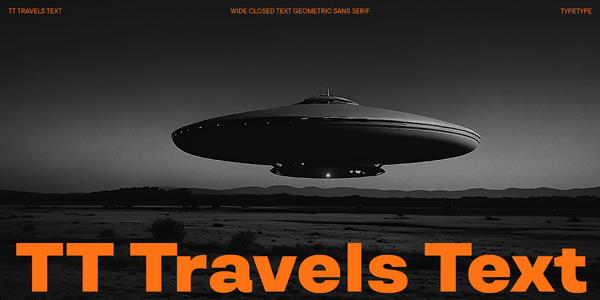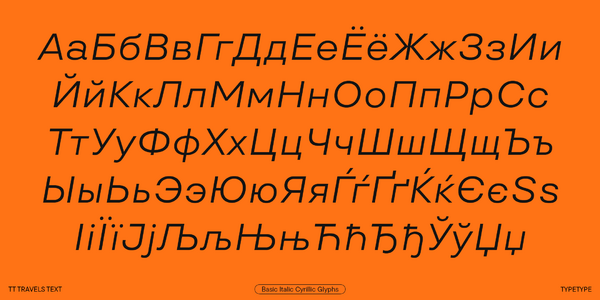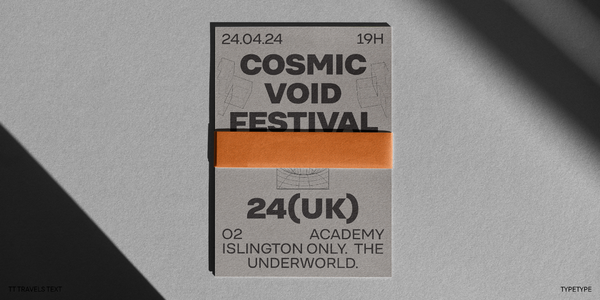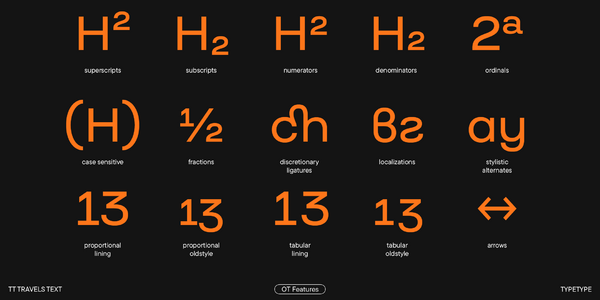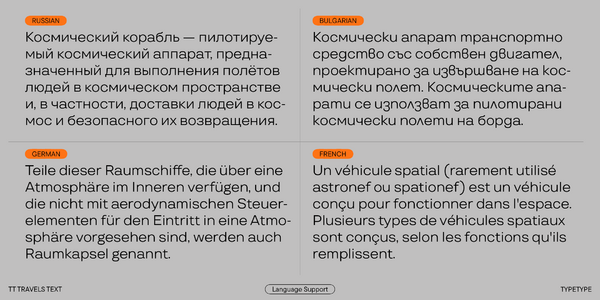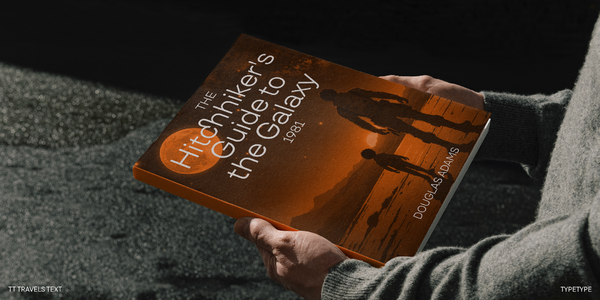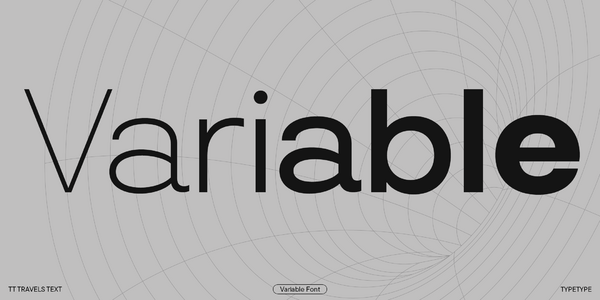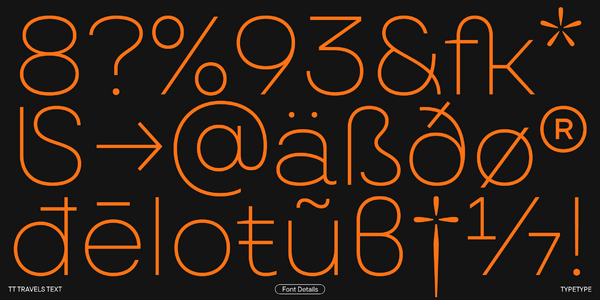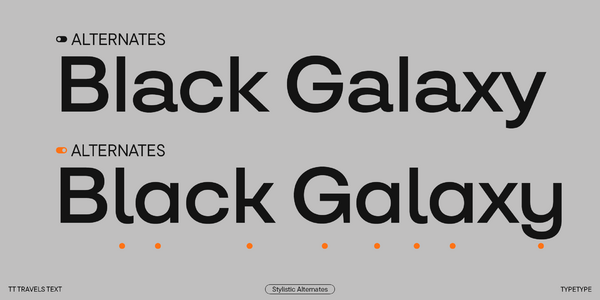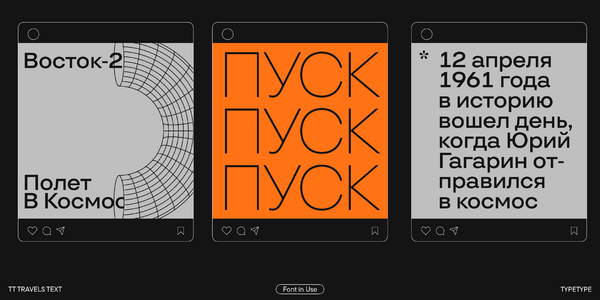
TT Travels Text
TT Travels Text — ТТ Травелс Текст
Произносится «ТТ Травелс Текст». «Travels» — производное слово от travel, в переводе с английского «путешествие», «Text» — в переводе с английского «текст». Буквы «TT» являются аббревиатурой названия компании.
TT Travels Text — геометрический гротеск с широкими пропорциями. Это универсальный и стильный текстовый шрифт.
Универсальный текстовый гротеск для любого проекта
TT Travels Text — это полная и детальная реинкарнация легендарного TT Travels. В новой гарнитуре количество начертаний увеличилось с 18 до 20, а кассовый состав расширился практически вдвое. Мы добавили новые OpenType фичи, что дало шрифту еще больше дополнительных возможностей. Также мы привели в порядок каждый контур и внедрили в гарнитуру все последние наработки, которые появились в нашей студии за прошедшие годы. Фактически мы создали новый текстовый гротеск, который станет универсальной рабочей лошадкой в любом вашем проекте.
Геометрический, текстовый, нейтральный
О гарнитуре TT Travels Text
Встречайте TT Travels Text — новый универсальный текстовый шрифт от TypeType, созданный на базе легендарного TT Travels.
TT Travels Text — геометрический гротеск с широкими пропорциями. Создавая этот шрифт, мы стремились сохранить основную идею и узнаваемые черты уже знакомого вам TT Travels, но сделать его более чистым и современным. В результате у нас получилась самостоятельная гарнитура, которая не только станет идеальной текстовой парой для TT Travels Next, но и отлично умеет работать соло.
Основные визуальные отличия TT Travels Text — достаточно широкие пропорции и немного сквадраченные формы овалов. Чтобы шрифт хорошо читался, мы сделали высоту строчных знаков выше, чем в исходном TT Travels, а апертуру — более открытой. Также мы поработали с пропорциями и контурами, немного заузили формы овалов и переработали толщины мастеров, чтобы в паре с TT Travels Next текстовая версия смотрелась гармонично. А еще — избавились от ловушек для чернил в жирном начертании: так шрифт стал более нейтральным и современным.
В новый TT Travels Text мы заложили множество полезных OpenType фич. Среди стилистических сетов вы найдете более мягкие и нейтральные формы. Графика расширенного набора лигатур также стала спокойной и плавной, поддерживающей настроение шрифта. А еще гарнитура включает вариативный шрифт, меняющийся по двум осям, что еще больше расширяет возможности ее применения.
Благодаря особенностям графики, которые мы перечислили выше, TT Travels Text можно использовать не только в массивах текста, но также в айдентике, вебе и печати — как самостоятельный графический акцент. Шрифт будет гармонично смотреться в верстке книг и журналов, на плакатах и афишах, в дизайне упаковки. При этом благодаря нейтральному характеру сфера его применения не ограничена, а в паре с TT Travels Next шрифт раскрывает весь свой потенциал.
TT Travels Text — это:
• 21 начертание: 10 прямых, 10 наклонных и 1 вариативный шрифт, меняющийся по осям наклона и жирности;
• 990 глифов в каждом начертании;
• 37 OpenType фич, в том числе возможность менять некоторые формы на альтернативные;
• Поддержка более 230 языков.
TT Travels Text — стильный текстовый гротеск для любого проекта!
ss01 | Alternative I
I Í Î
ss02 | Alt. Latin K, k and Cyrillic Zhe, zhe, K, k
Җ Ķ ќ
ss03 | Alternative G